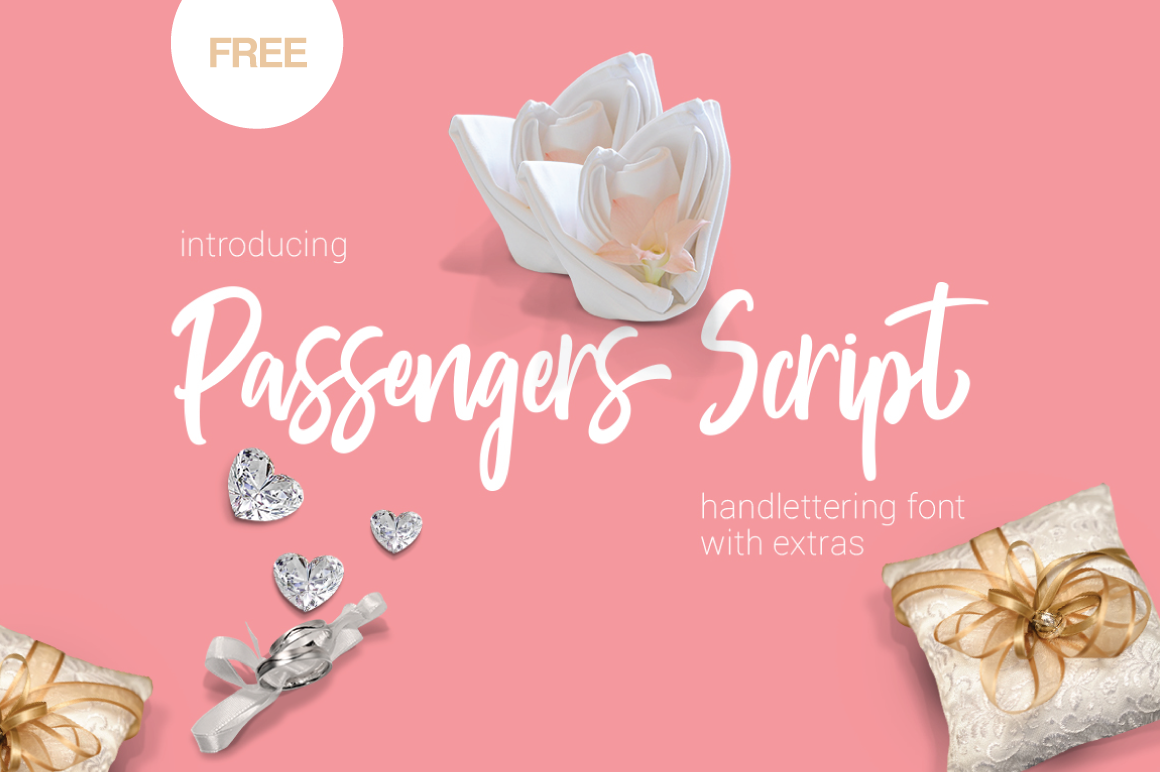
Aqui está uma descrição em português do Brasil para a página de download da fonte ‘Passengers Script Font’, seguindo as instruções: Começando uma nova semana com um novo font livre, apresentamos Passengers Script Font! Esta elegante e singular fonte cursiva foi criada pelo Pathero Studio. Ela traz o charme clássico num total de 300 caracteres únicos. Ideal para diversas aplicações, como logotipos, cartões de casamento, cabeçalhos, camisetas, carimbos, rótulos, publicações, cartazes e até mesmo impressões de notícias, o Passengers Script é uma fonte única que tornará seus projetos ainda mais especiais. Com sua facilidade na escrita manual incorporada, esta fonte é perfeita para aqueles buscando algo único e autêntico para dar um toque especial a seus materiais. Inclua este charme handwritten em seus próximos trabalhos ou projetos e deixe seu trabalho brilhar ainda mais. Sempre lembre-se: o estilo e personalidade de uma fonte podem transformar a maneira como sua mensagem é recebida. Passengers Script Font é a escolha perfeita para quem busca algo diferente e emocionante em cada projeto.